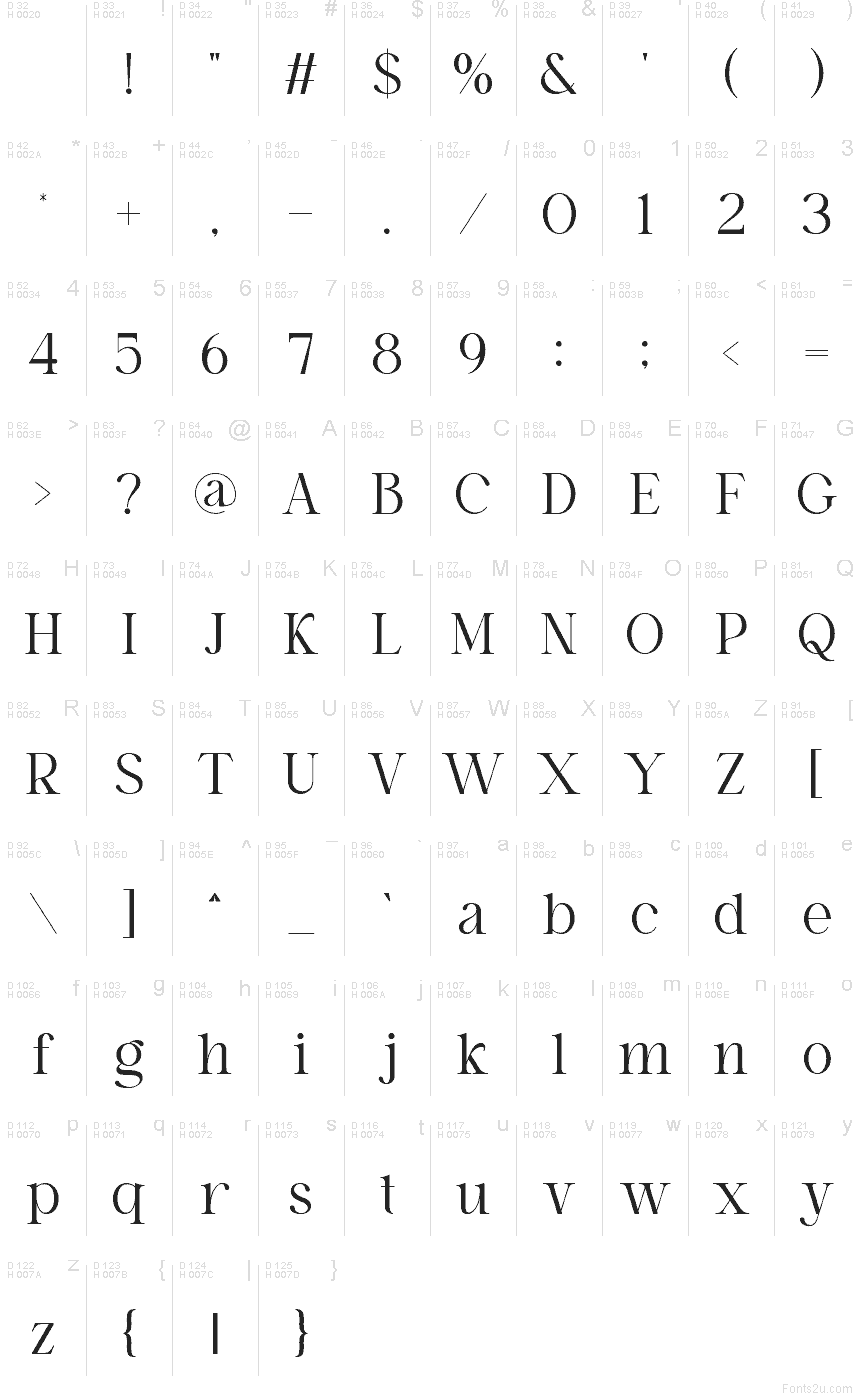
Bolsgi Regular
Písmo Bolsgi od ErmediaStudio je bezplatný font so serifmi, ktorý spája ostrosť a eleganciu s nečakane jemnými krivkami. Jeho široké, atramentové ťahy sa vpíjajú do zaoblených, takmer kvapkovitých zakončení, vďaka čomu má každé slovo rytmus, ktorý pôsobí redakčne a zároveň ručne vypracovane. Písmená sú blízko seba a majú sebavedomý, mierne dramatický výraz, takže aj krátke slovo vyzerá štýlovo a premyslene.
Pri použití Bolsgi získajú nadpisy a logotypy luxusný, umelecký nádych, ktorý vynikne v identitách značiek, časopisoch, na obaloch, knižných obálkach aj v portfóliách. Tento bezplatný font najlepšie vynikne vo veľkých veľkostiach, kde môžu jeho vygravírované krivky dýchať; skombinujte ho s čistým geometrickým bezpätkovým písmom v hlavnom texte a získate bohatý, moderný kontrast, ktorý stále pôsobí ucelene a rafinovane.